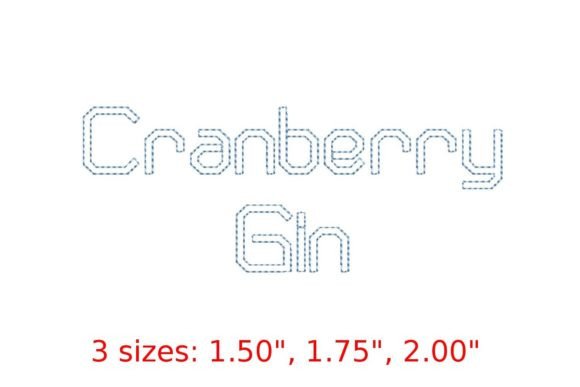
Cranberry Gin Bean Stitch Outline Font
適切なデザイン要素を見つけるのは難しい場合がありますが、Cranberry Gin Bean Stitch Outline Fontは作品を即座に引き立てる優れたコレクションを提供します。
POD(オンデマンド印刷)製品、結婚式の招待状、またはソーシャルメディアのグラフィックを作成している場合でも、Cranberry Gin Bean Stitch Outline Fontは理想的です。
専門家のヒント:これらの要素を補完的なフォントと組み合わせて、市場で際立つユニークで目を引くデザインを作成します。